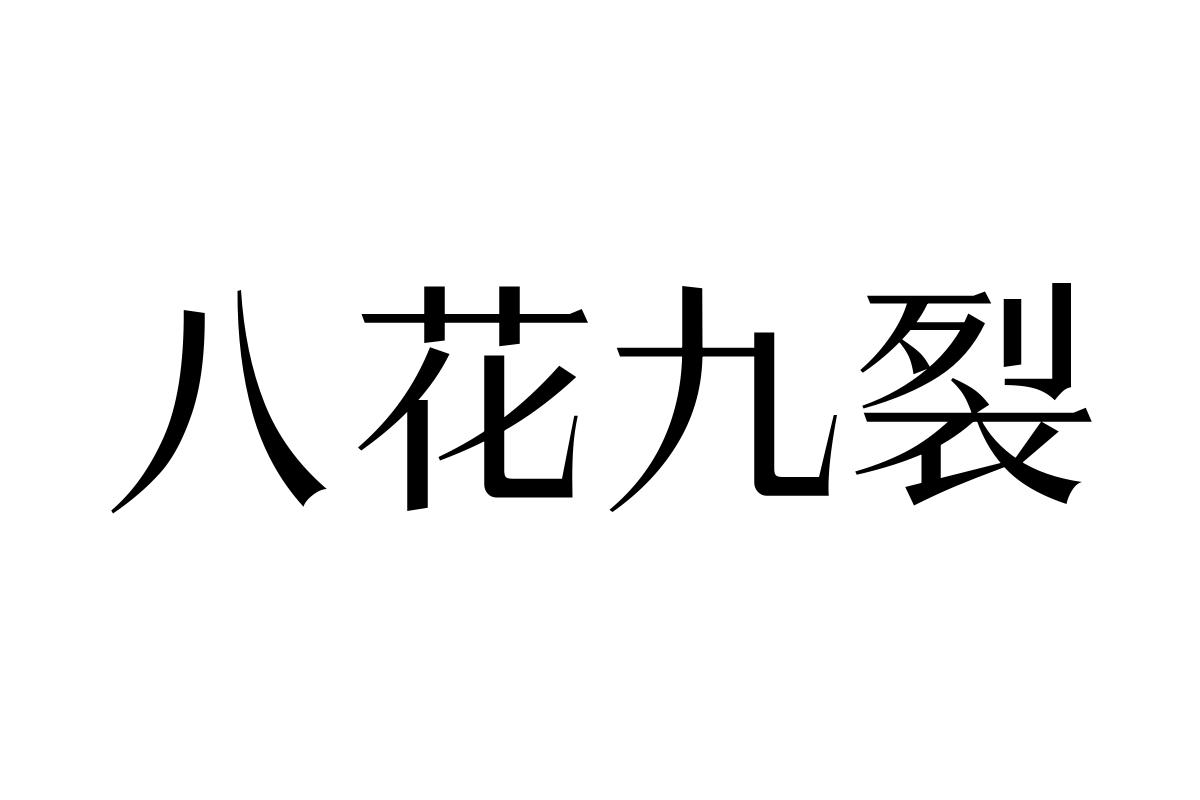
三极黑宋体细是一种具有独特风格的中文字体,它结合了传统的宋体字和现代的黑色字体设计元素。这种字体的特点是笔画粗细不一,线条流畅,给人一种优雅而精致的感觉。
在设计上,三极黑宋体细采用了简洁的线条和结构,使得整体看起来更加清晰和易于阅读。它的字形大小适中,既适合用于标题和正文,又可以用于各种类型的文本内容。
此外,这种字体的笔画粗细变化丰富,既有细腻的线条,又有粗犷的笔画,使得整个字体呈现出一种独特的美感。同时,它还具有一定的可读性,无论是在正式的文件还是非正式的社交媒体上,都能展现出其独特的魅力。
总的来说,三极黑宋体细是一种非常适合用于商业、广告、杂志等场合的字体,它可以为设计作品增添一份独特的个性和品味。